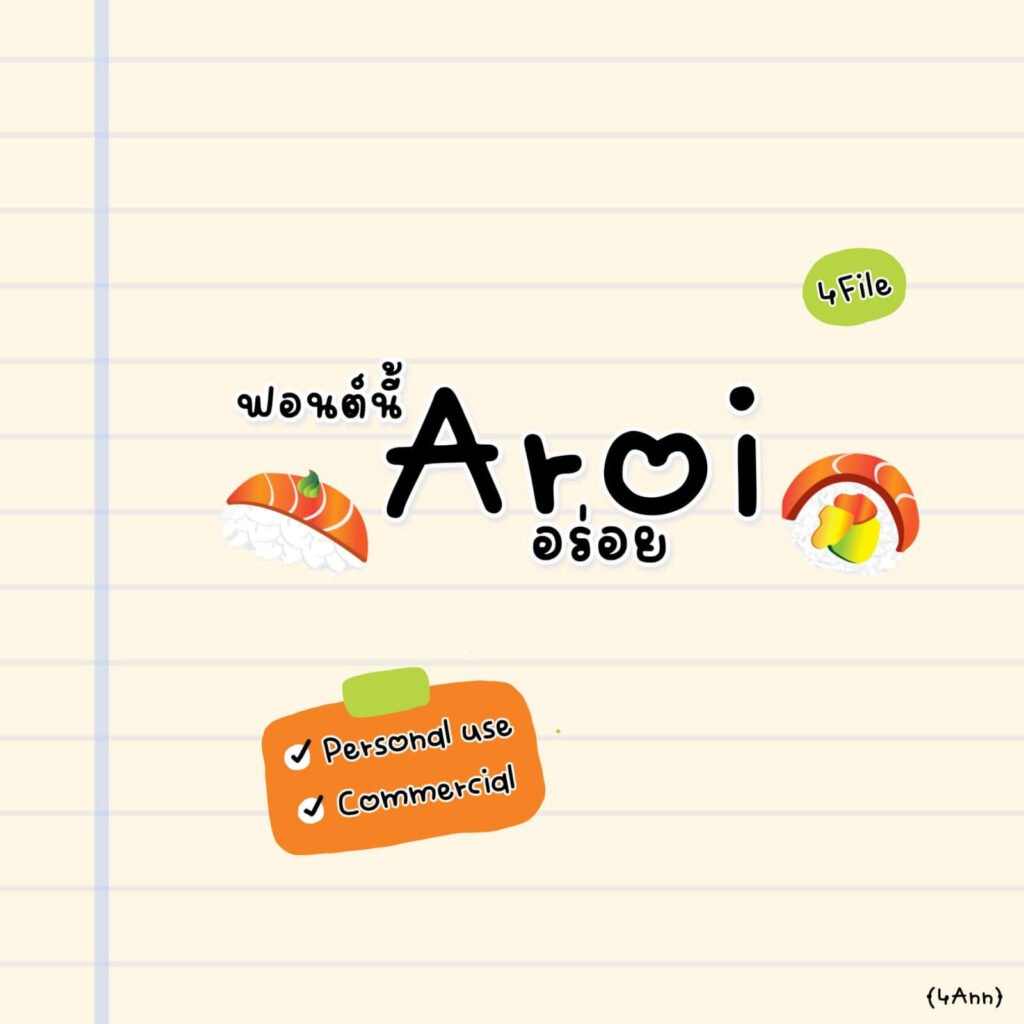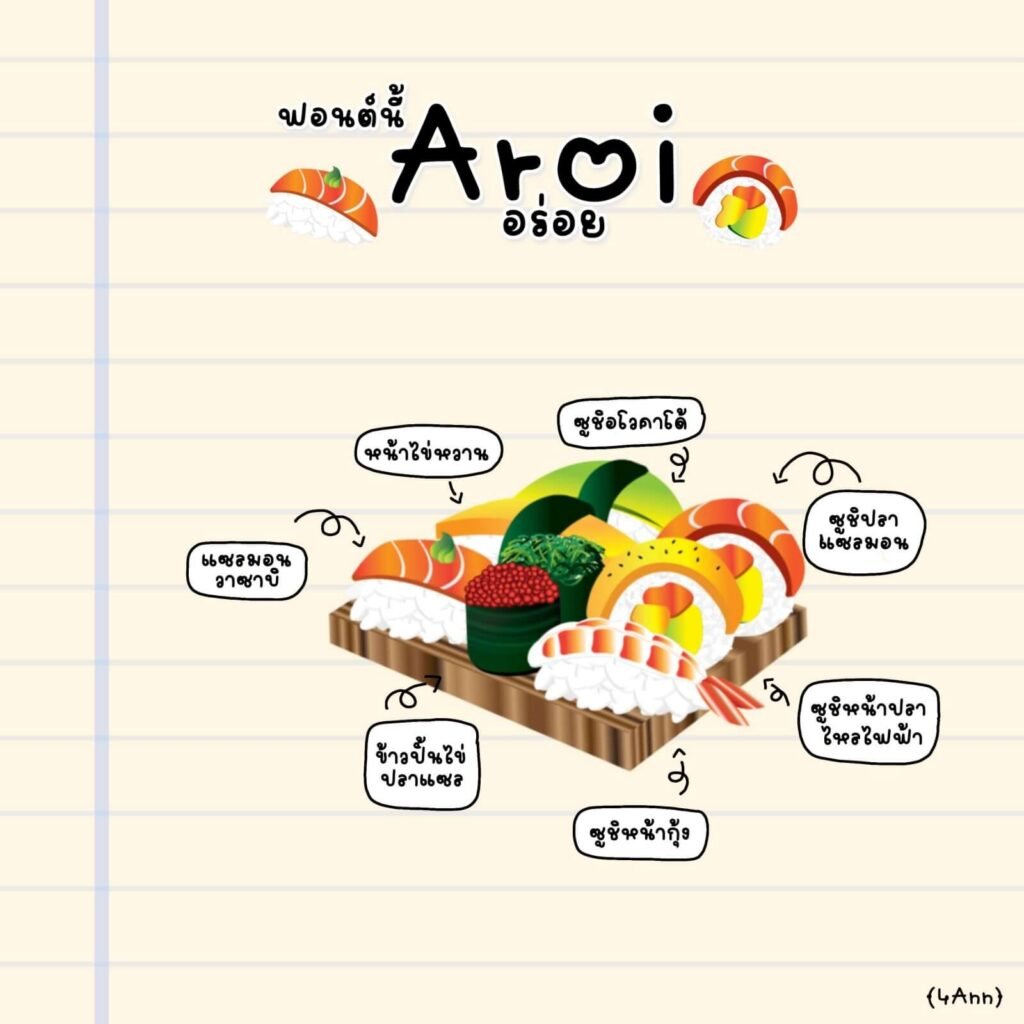
อร่อย (4AnnAroi)
แจกฟรี! 1 น้ำหนัก สำหรับใช้งานส่วนตัว *สามารถนำไปทำคลิปได้ทุกประเภท* Font 4AnnAroi มี 4 ไฟล์ 4 น้ำหนัก ฟอนต์แนววัยรุ่น น่ารัก เรียบง่าย ทันสมัย เรียบร้อยไม่มาก แต่อ่านง่าย ยังเหมาะกับรายละเอียดเยอะๆ เหมือนเดิมค่ะ หรือจะใช้แค่คำสั้นๆ ก็น่ารัก อมเปรี้ยว อมหวาน ฝากเอ็นดูน้องด้วยค่า